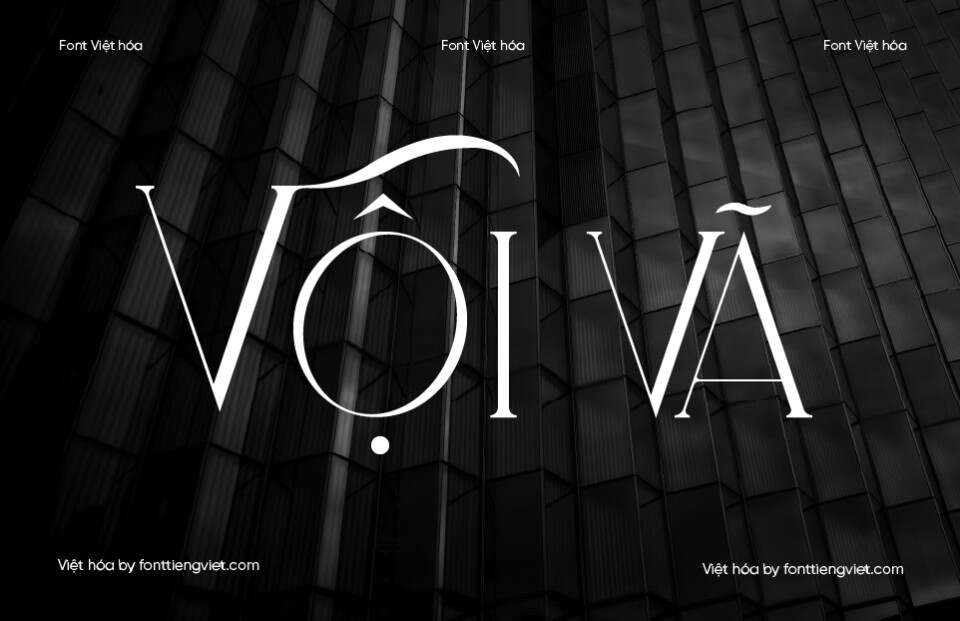
Font Việt hóa 1FTV VIP Bontias
Font Việt hóa 1FTV VIP Bontias – Sự kết hợp hoàn hảo giữa cổ điển và hiện đại trong thiết kế
Giới thiệu về Font Việt hóa 1FTV VIP Bontias
Trong thế giới đồ họa, việc lựa chọn một bộ Font Miễn Phí phù hợp đóng vai trò quyết định đến sự thành công của một tác phẩm nghệ thuật. Font Việt hóa 1FTV VIP Bontias là một lựa chọn xuất sắc dành cho những ai đang tìm kiếm sự tinh tế và thanh lịch. Đây là phiên bản được tối ưu hóa hoàn toàn cho tiếng Việt, giúp người dùng không còn lo lắng về lỗi hiển thị dấu hay khoảng cách chữ khi thiết kế các ấn phẩm quan trọng.
Tại sao nên sử dụng Font Việt hóa 1FTV VIP Bontias?
Bộ font này mang phong cách Serif (có chân) cổ điển nhưng được cách điệu theo hướng hiện đại, tạo nên vẻ ngoài sang trọng và chuyên nghiệp. Font Việt hóa 1FTV VIP Bontias không chỉ thu hút bởi những đường nét uốn lượn mềm mại mà còn bởi tính ứng dụng cao. Các nhà thiết kế thường ưu tiên sử dụng nó trong việc dàn trang tạp chí, thiết kế bìa sách giáo khoa, hoặc các tài liệu giảng dạy cần sự trang trọng và chỉn chu nhất định.
Ứng dụng thực tế của bộ font này trong thiết kế
Với cấu trúc ký tự rõ ràng, bộ font này giúp cải thiện trải nghiệm đọc một cách đáng kể. Trong môi trường học đường, các bạn học sinh có thể dùng nó để làm bài thuyết trình thêm ấn tượng. Trong khi đó, các giáo viên dễ dàng tạo ra những bộ tài liệu học tập đẹp mắt, khơi gợi cảm hứng cho học sinh. Khả năng tương thích tốt trên nhiều phần mềm đồ họa giúp quá trình sáng tạo trở nên mượt mà hơn bao giờ hết.